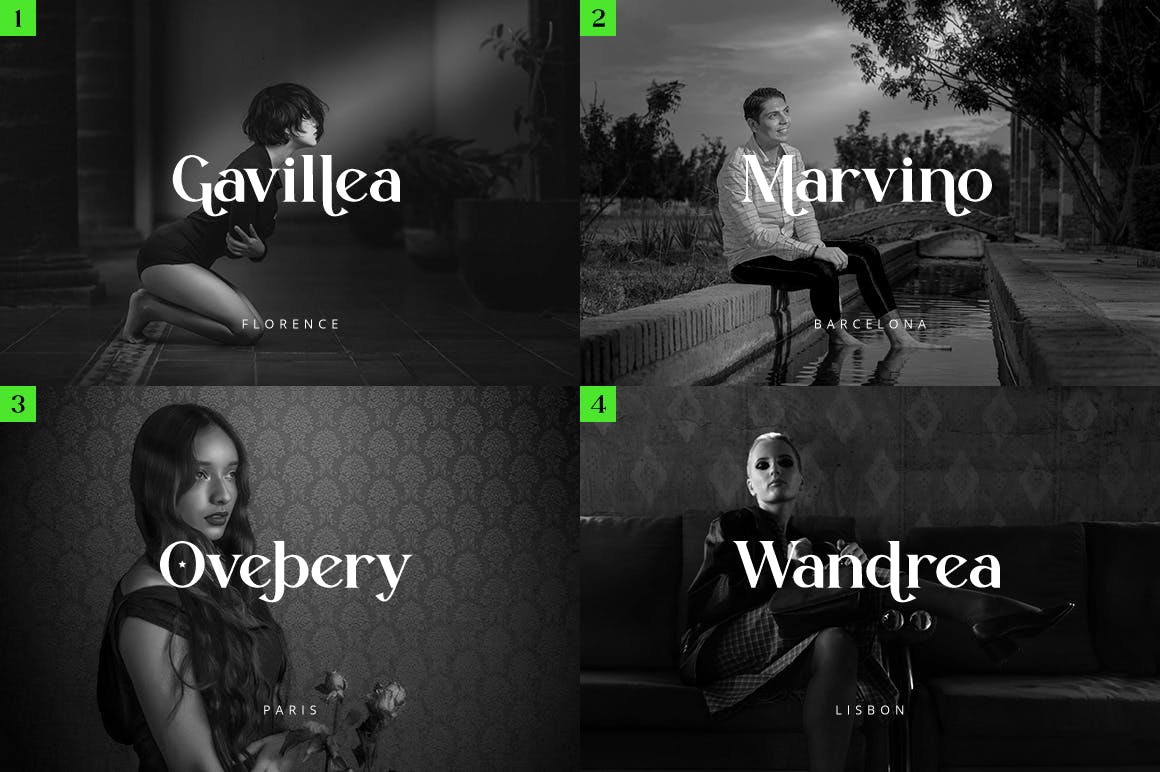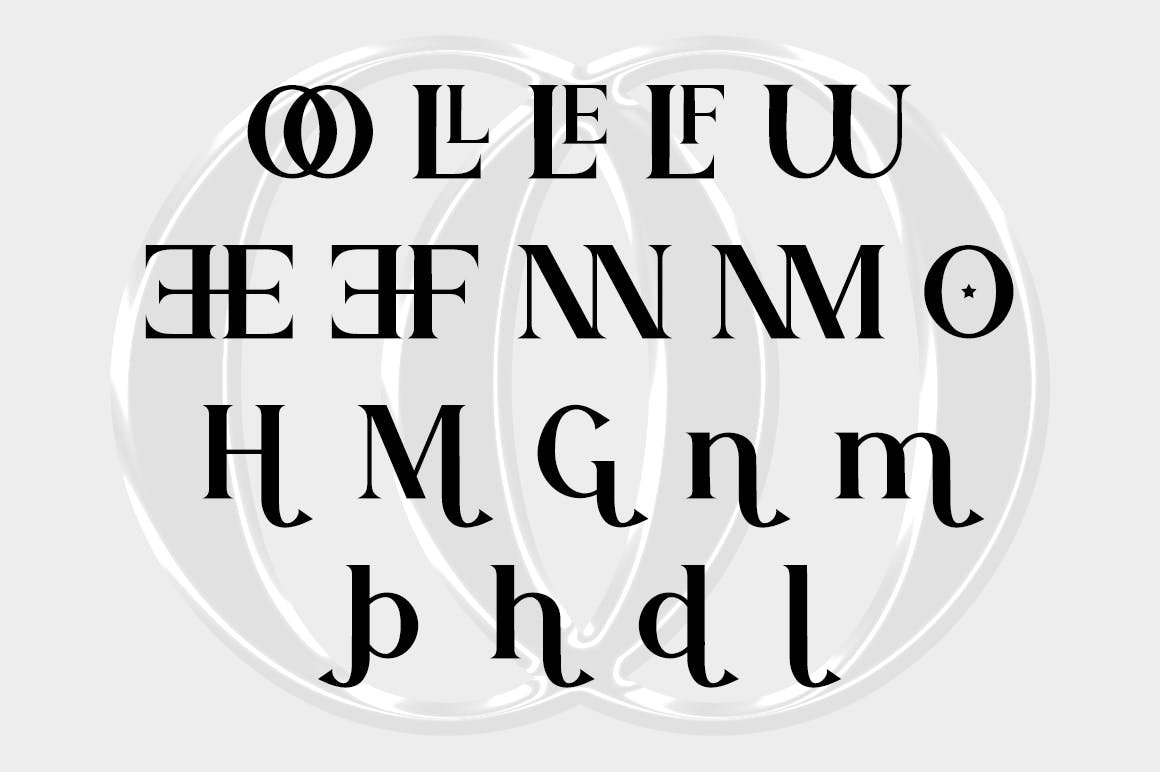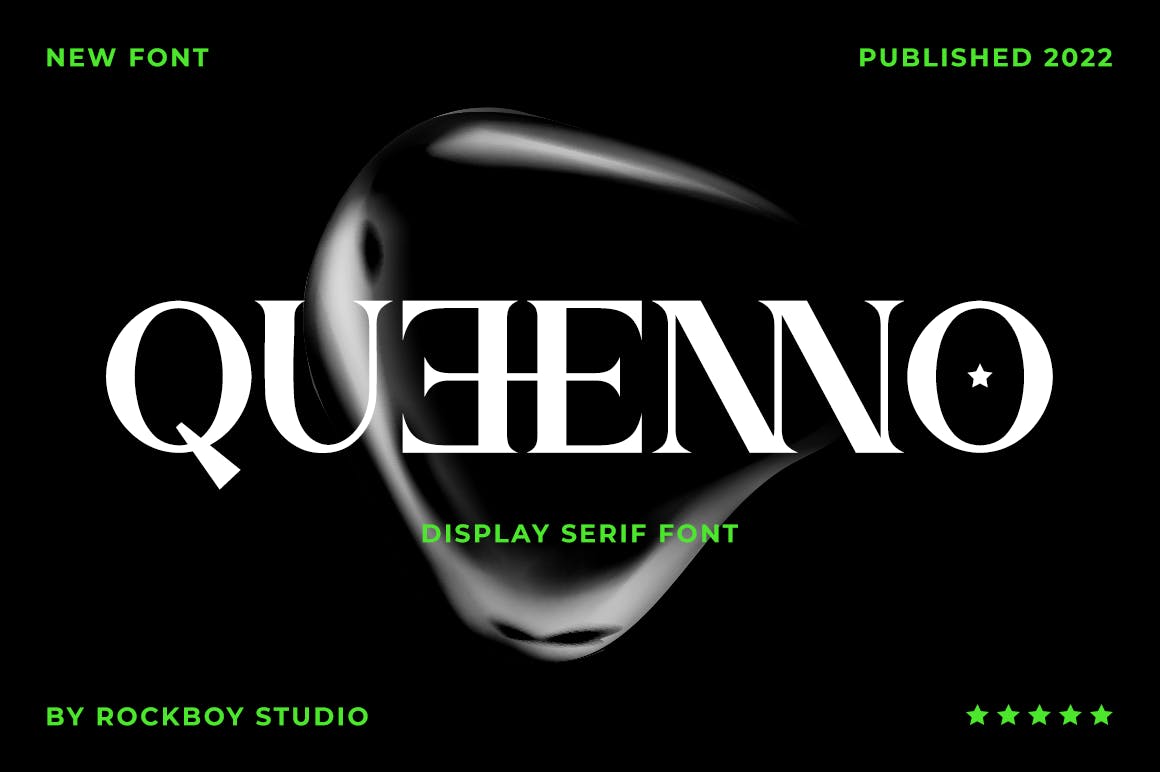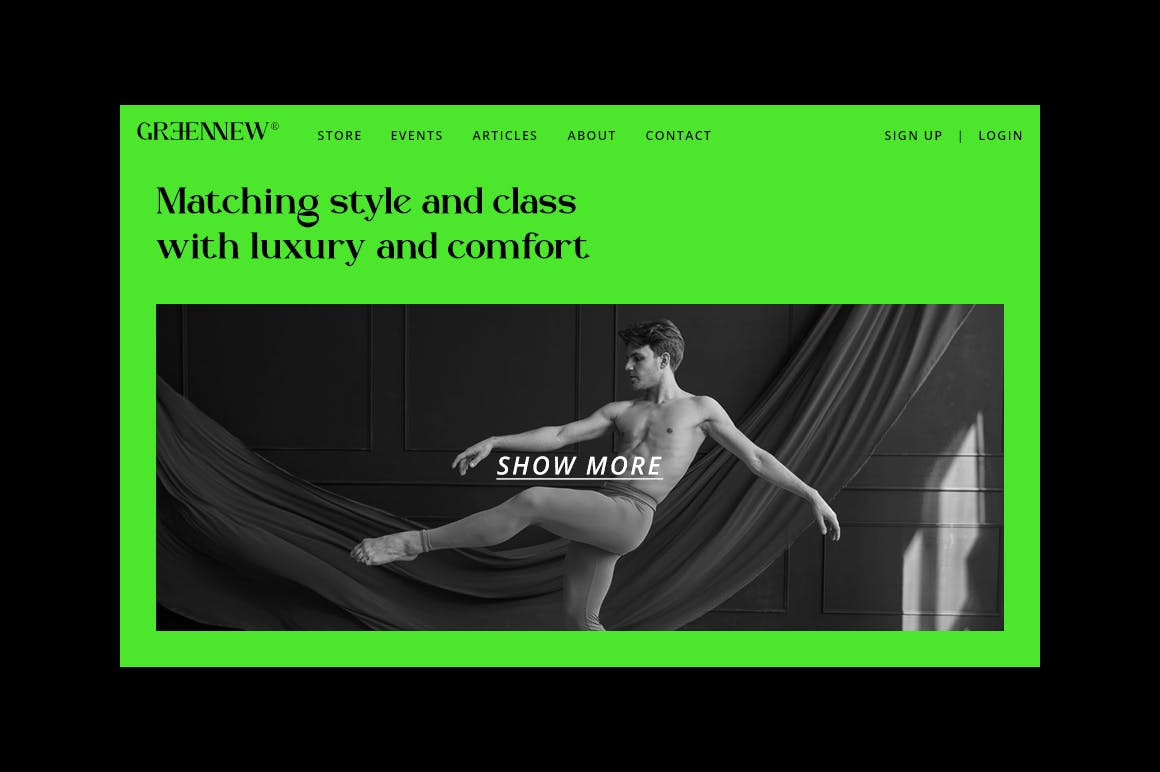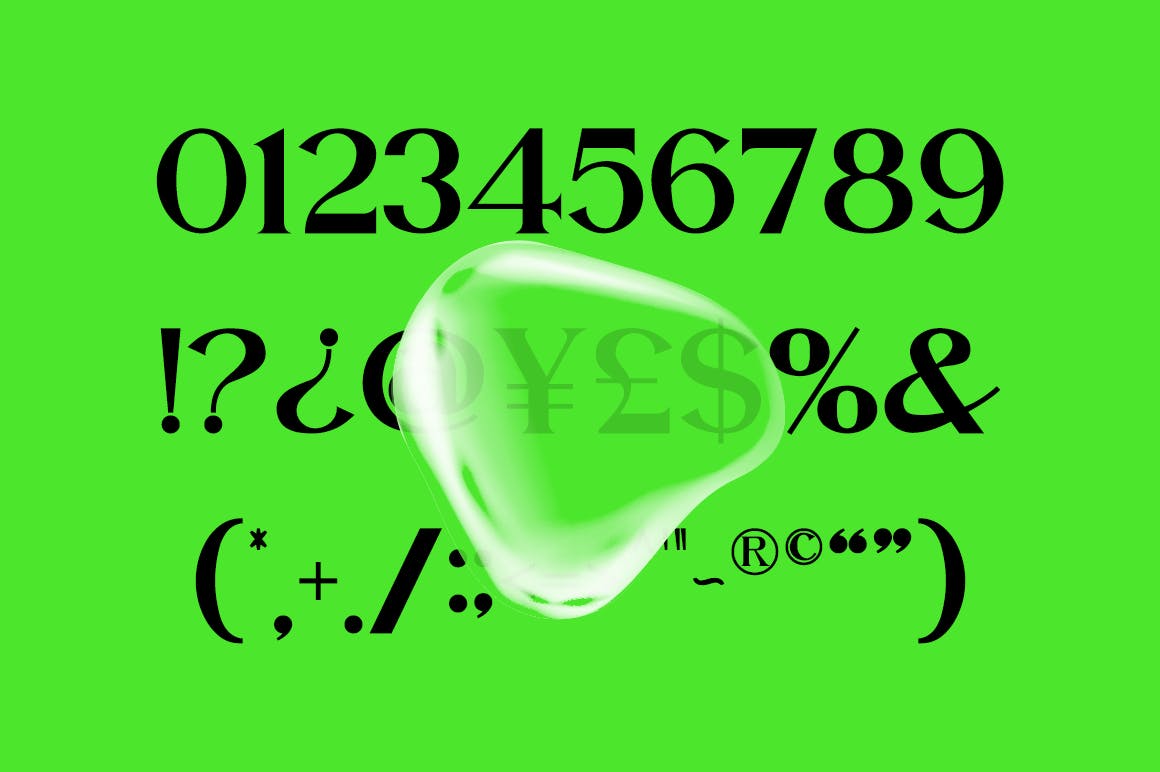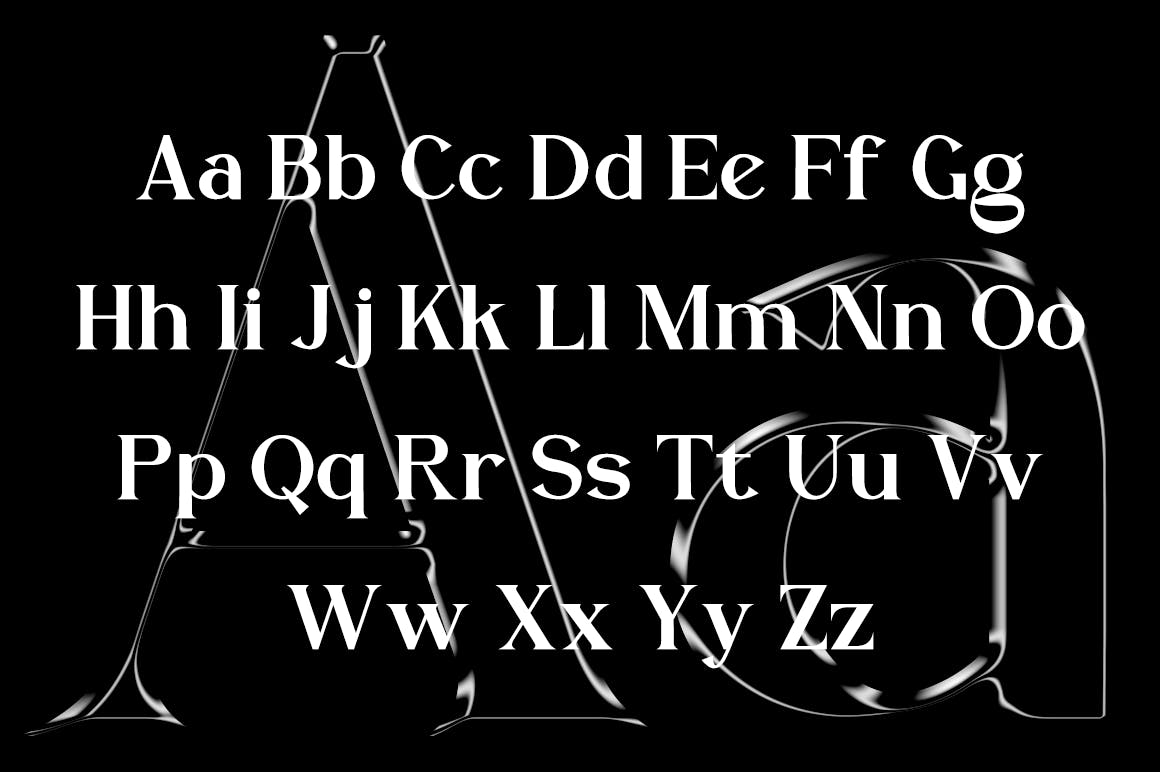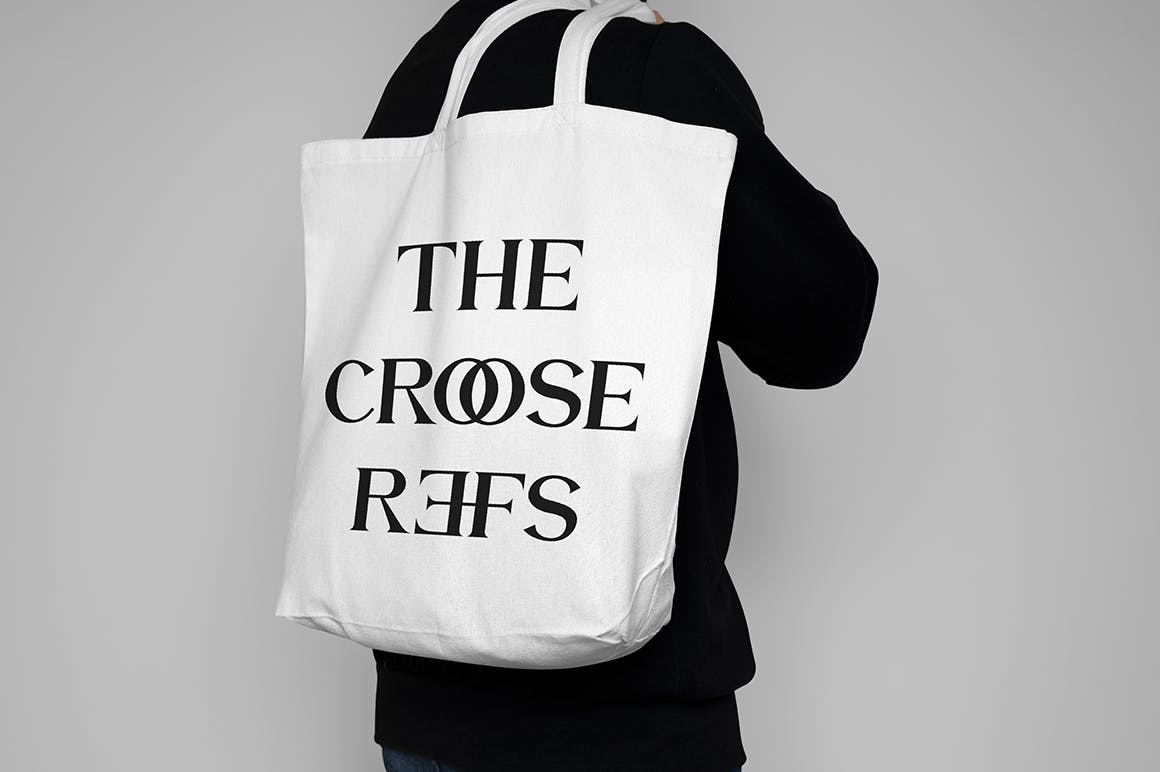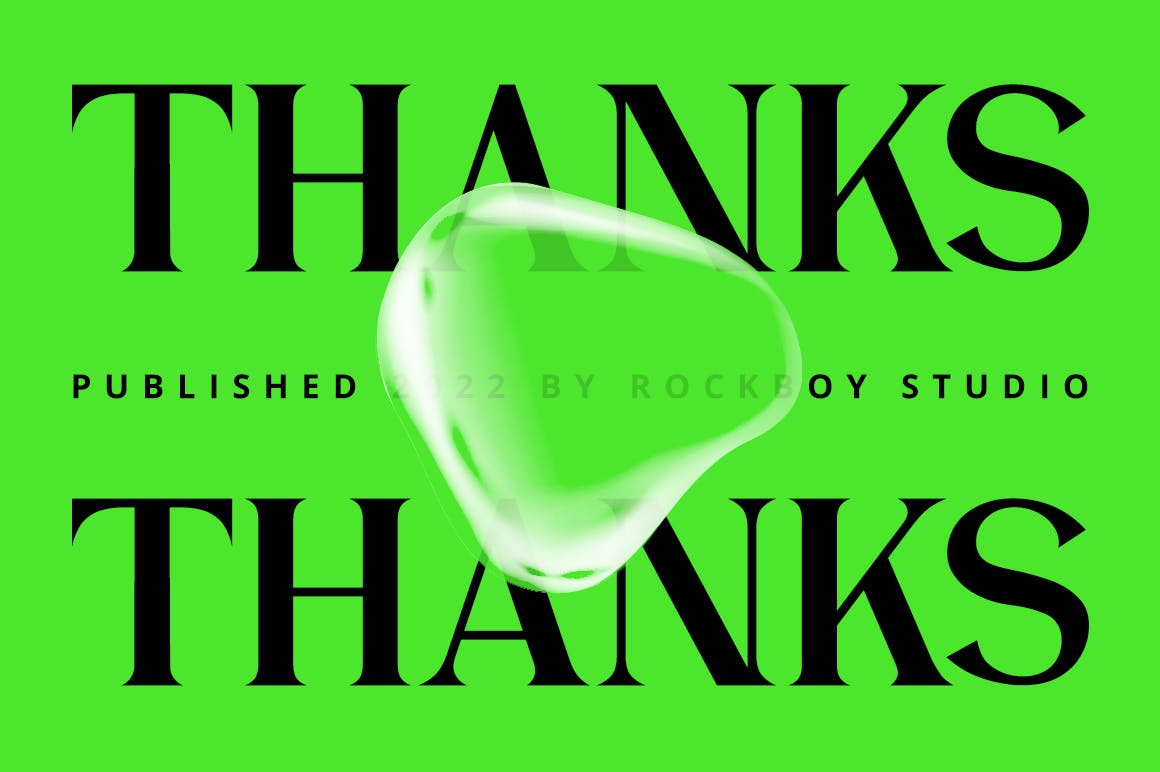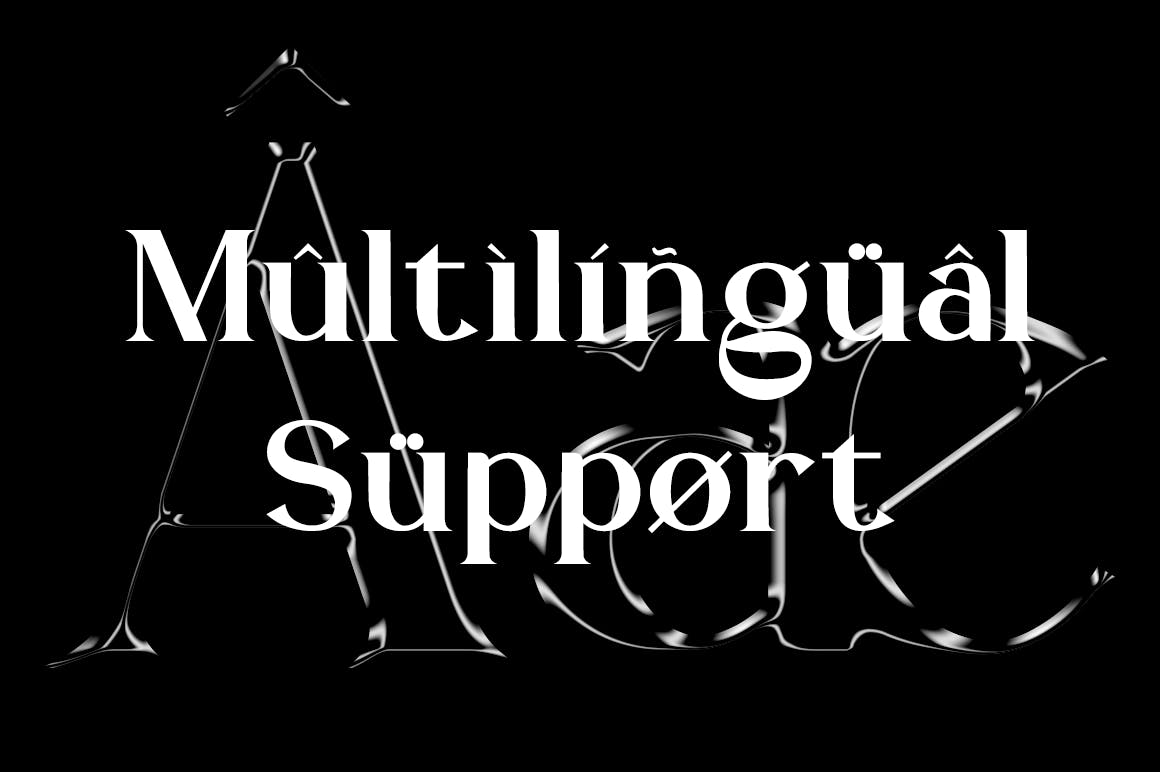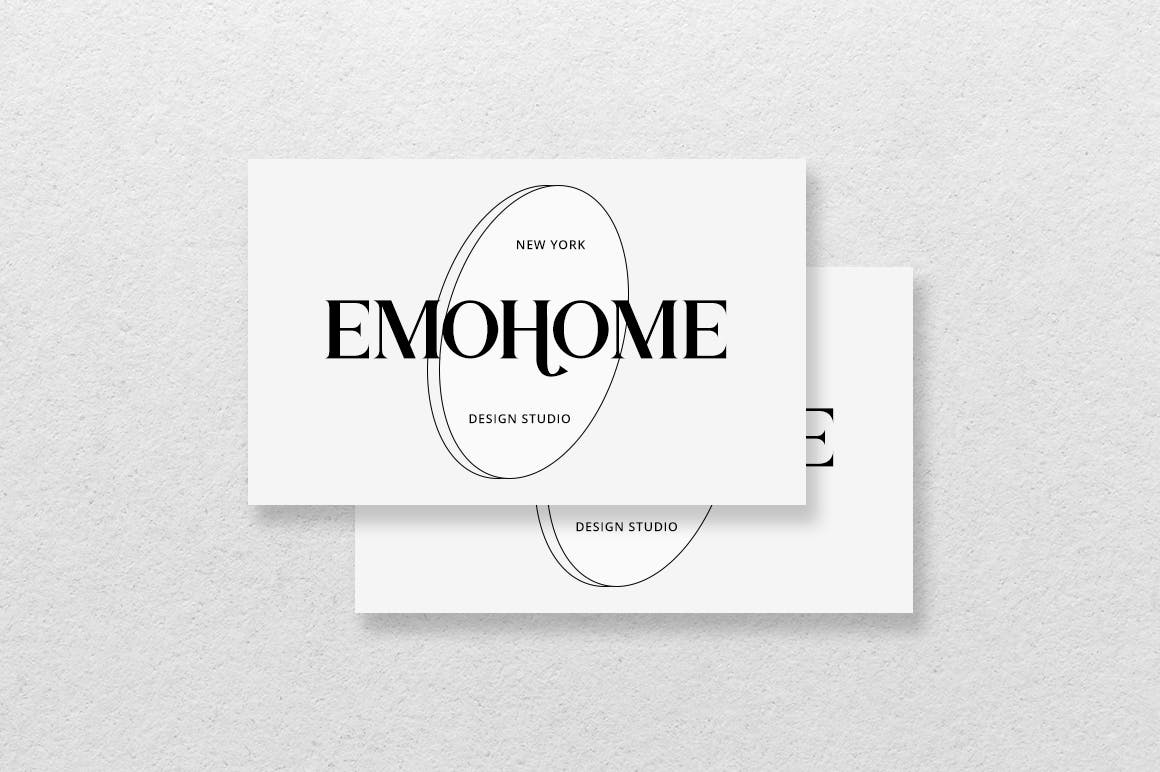
Queenno یک فونت سریف منحصر به فرد، شیک و اصیل است. این فونت با طراحی ماهرانه، به یکی از انتخابهای محبوب شما تبدیل خواهد شد و توانایی ارتقاء ایدههای خلاقانه شما را به بالاترین سطح دارد!